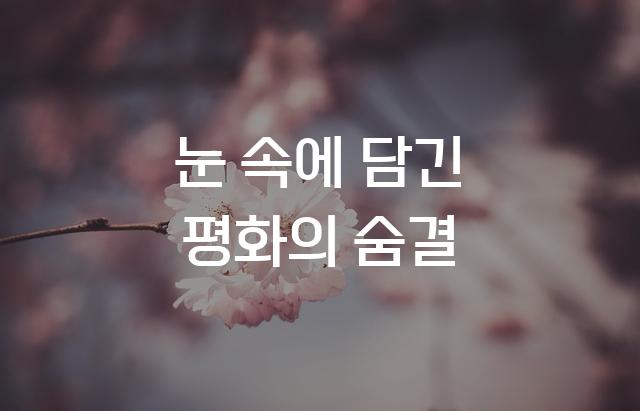
평창평화체는 기본 고딕 스타일에 네모난 형태를 가진 독특한 제목용 폰트입니다. 별모양 디테일이 포함되어 있어 창의적이고 평화로운 느낌을 줍니다.
평창평화체은(는)
별모양/패턴, 길고/크고, 기본 고딕, 부드러움, 단단함, 감성적인, 네모꼴, 레트로 계열의 생김새를 가지고 있으며
교육 자료, 출판물 제목, 프레젠테이션 등에서 자주 활용되며, 효과적인 메시지 전달에 적합합니다.
이 폰트는 교육, 문화/예술, 공공/정부 분야에 잘 어울리며,
편안한, 신뢰감, 감성적인 느낌을 담고 있는 것이 특징입니다.